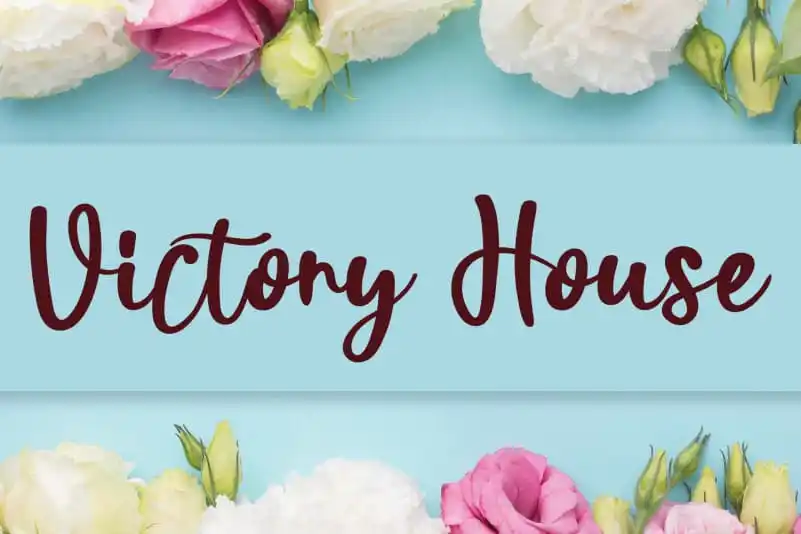
Victory House Script Font – Download Grátis
A ‘Victory House Script Font’ é uma elegante fónta escrita a mão que transmite uma sensação romântica e autêntica do Brasil. Embora não seja específica à nossa cultura, sua natureza fluida e sofisticada se encaixa perfeitamente com o estilo brasileiro de criatividade expressiva. Perfeita para adicionar um toque delicado às suas criações gráficas, ela é especialmente apropriada para projetos que valorizam a simplicidade do design handwritten, como logotipos, anúncios ou até mesmo ilustrações em estilo vintage. Quer seja o amanhã da sua marca digital, um e-mail personalizado com o sabor de nossa cultura brasileira, ou uma peça de arte decorativa em seu lar, a ‘Victory House Script Font’ proporciona uma mão-dilhada para alcançar esses sonhos. E ela não só oferece essa capacidade, mas faz isso com uma estética que remete a dias antigos, quando o handmade ainda tinha lugar no coração de quem projetava e criava. Através dela, você pode transformar sua ideia em um design único, resgatando algo autêntico do nosso passado ao criar futuros impecáveis.